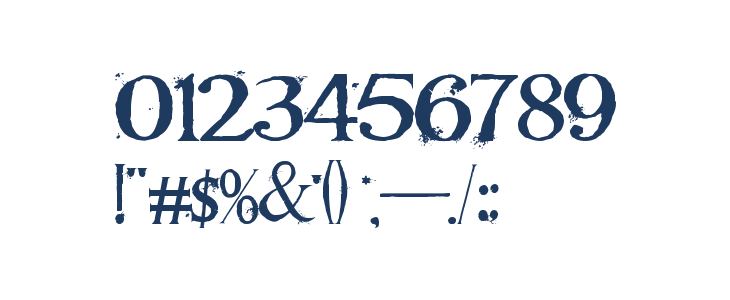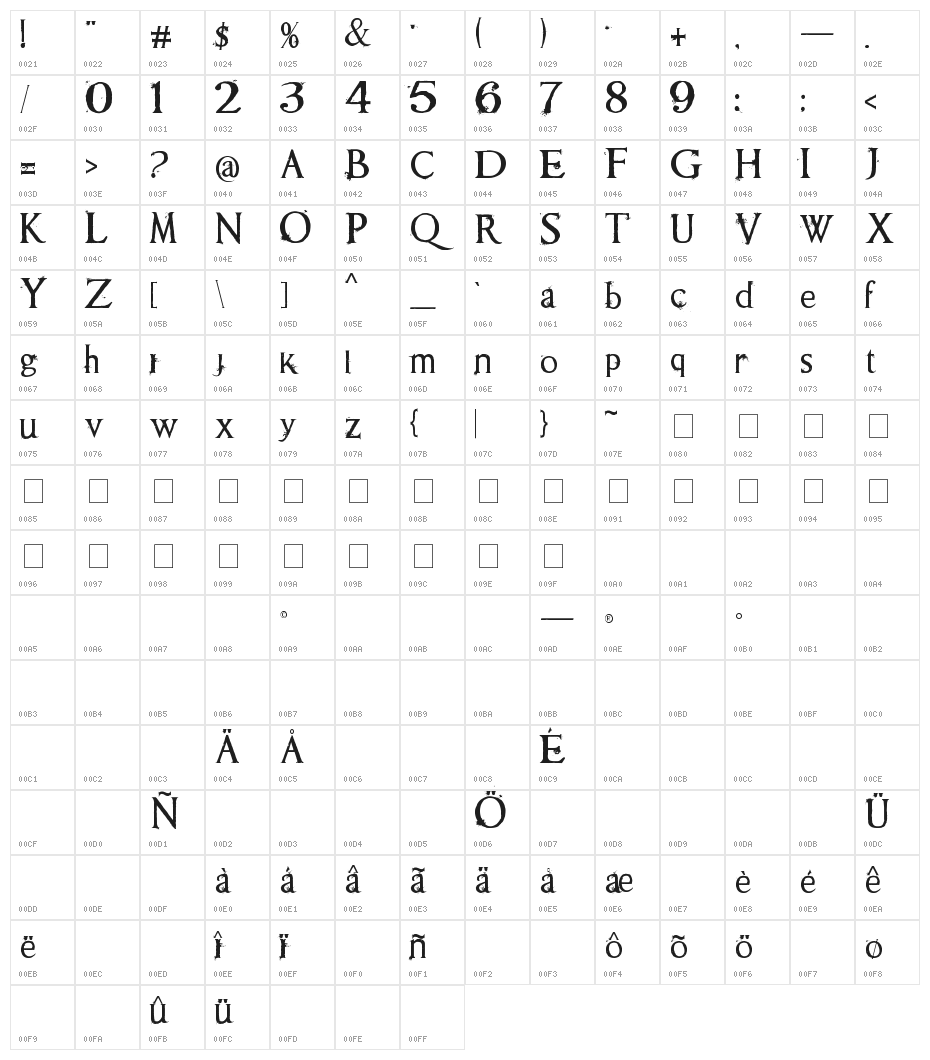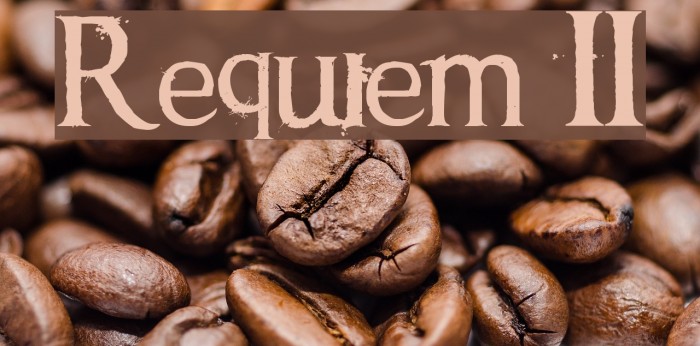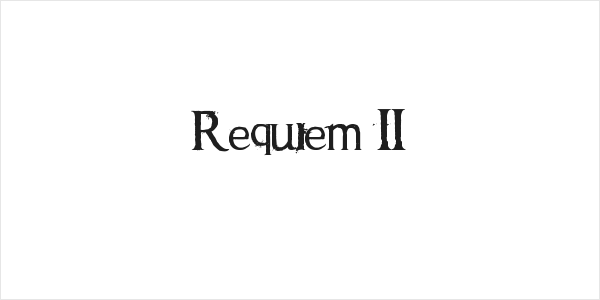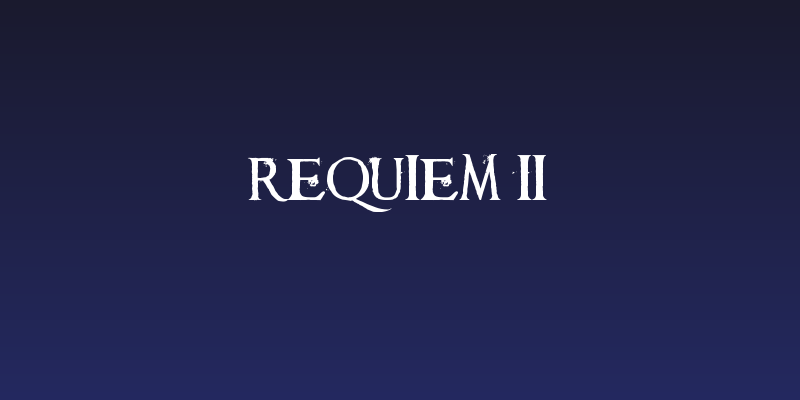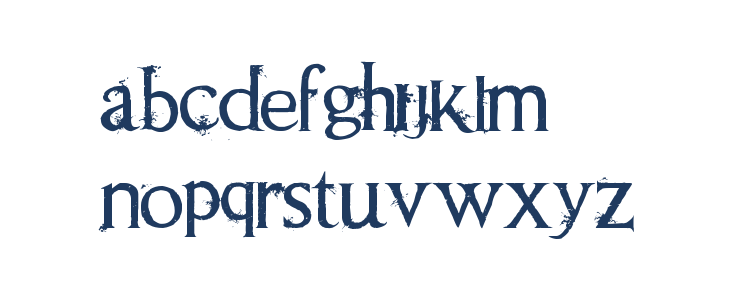
Requiem II Font
✎ Serif
| Categorie | Serif |
| Caso d'uso | Headlines, Logos, Artistic projects |
| Progetti proposti | Ideal for projects that require a vintage or artistic touch, such as posters, album covers, or branding for creative industries. |